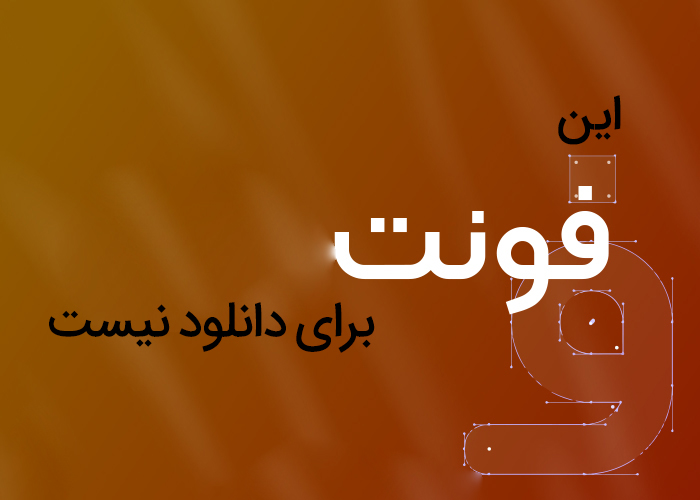
فونت مربع
اگر نیاز به یه فونت ساده و زیبا دارید بهترین انتخاب فونت  فارسی مربع است. برای دانلود فونت  فارسی مربع باید در سایت حساب کاربری ایجاد کنید پس از آن می‌توان با هر فرمتی که می‌خواهید فونت مربع را دانلود کرده و در پوستر خام از آن استفاده کنید.در فونت مربع از 4فرمت ttf-eot-woff2-woff استفاده شده است.همچنین فونت مربع فونتی است که برای عبارت های کوتاه طراحی شده است.برای دانلود طرح های گرافیکی کافیست روی لینک کلیک کنید .فونت مربع در دسته بندی فونت های فارسی قرار دارد. برای خریداری فونت مربع به سایت ایران فونت مراجعه کنید.